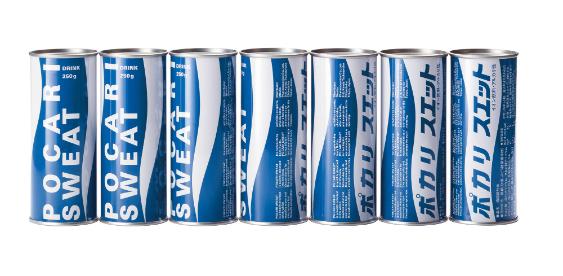
Helmut Schmid Typografie
DescriptionDie Typografie von Helmut Schmid ist präzise und elegant. Dies trifft insbesondere auf seine Logos für die japanische Pharma- und Kosmetikindustrie zu, aber auch auf seine Gestaltung der politischen Kampagnen für die deutsche SPD. Schmid machte Japan zu seiner Wahlheimat und verfeinerte unter dem Eindruck der dortigen Plakatkunst und der schlichten Schönheit japanischer Dinge den typografischen Ansatz seines Basler Lehrmeisters Emil Ruder. Die Ausstellung ist eine Hommage anlässlich der Donation seines Gesamtwerks. Sie zeigt die wichtigsten Stationen in Schmids Karriere und beleuchtet seine Position als Vermittler zwischen Ost und West. Zu sehen sind Logos, Verpackungen, Erscheinungsbilder und freie Arbeiten des Gestalters, der auch als Publizist international bekannt war.Object numberGBA-2024-D04-002